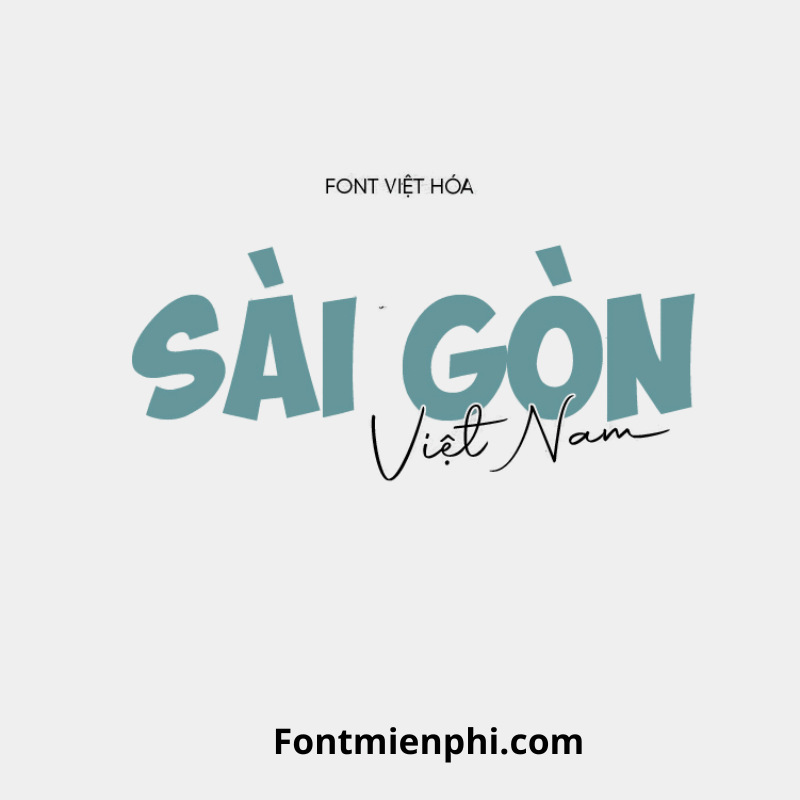
Font Việt hóa 1FTV VIP Obelix Pro regular
Font Việt Hóa 1FTV VIP Obelix Pro Regular – Phong Cách Chuyên Nghiệp, Đậm Nét Sáng Tạo
Font Việt hóa 1FTV VIP Obelix Pro Regular là một trong những kiểu chữ độc đáo, được thiết kế dành riêng cho ngôn ngữ Tiếng Việt. Với nét chữ cân đối, hiện đại và dễ đọc, font chữ này phù hợp cho nhiều mục đích thiết kế, từ in ấn đến quảng cáo, website.
• Thiết kế tinh tế: Obelix Pro Regular sở hữu nét chữ đều, mềm mại nhưng vẫn giữ được sự chắc chắn, phù hợp với tiêu đề và nội dung dài.
• Hỗ trợ Tiếng Việt: Font được Việt hóa hoàn chỉnh, bao gồm đầy đủ dấu và ký tự đặc biệt, đảm bảo hiển thị rõ ràng trên mọi nền tảng.
• Đa dụng: Phù hợp cho thiết kế logo, poster, bìa sách, banner, hoặc các dự án sáng tạo khác.
1FTV VIP Obelix Pro Regular là lựa chọn lý tưởng cho designer, marketer, và người làm content nhờ khả năng truyền tải thông điệp mạnh mẽ mà vẫn giữ tính thẩm mỹ cao.